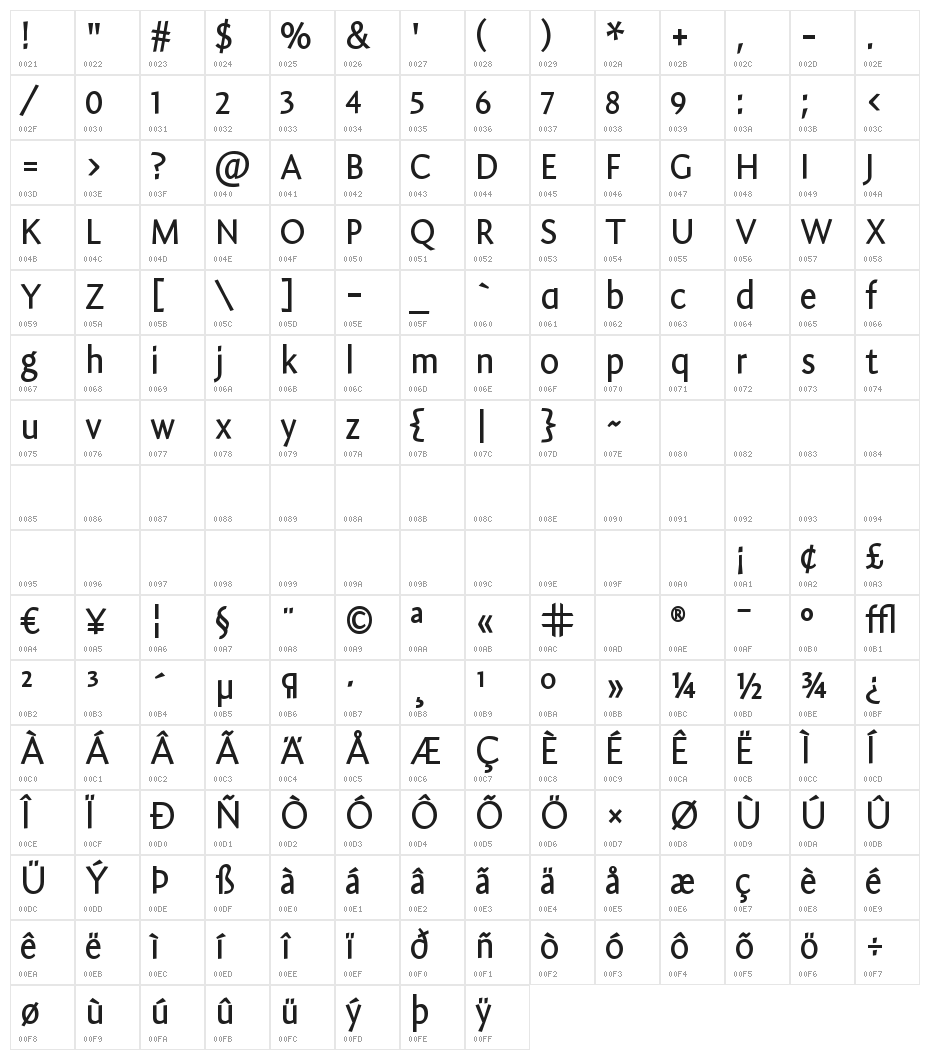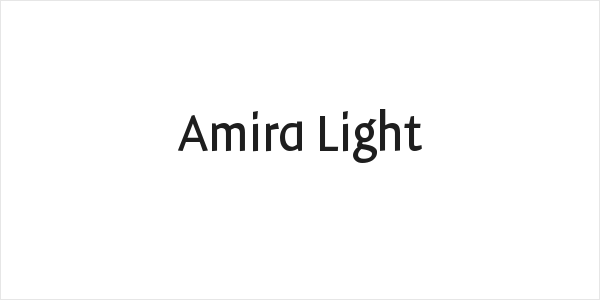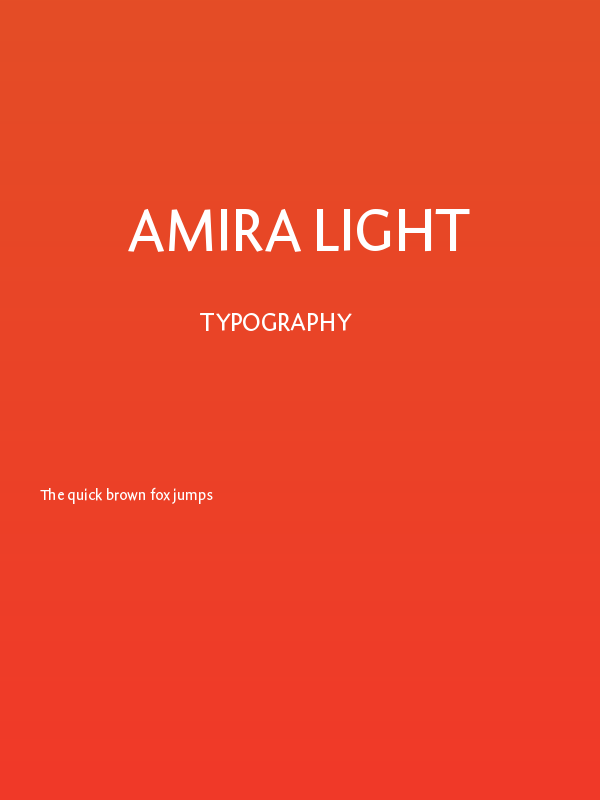
Amira Light Font
| Progetti proposti | Ideal for web design, branding, advertising, and editorial projects where clarity and modernity are essential. |